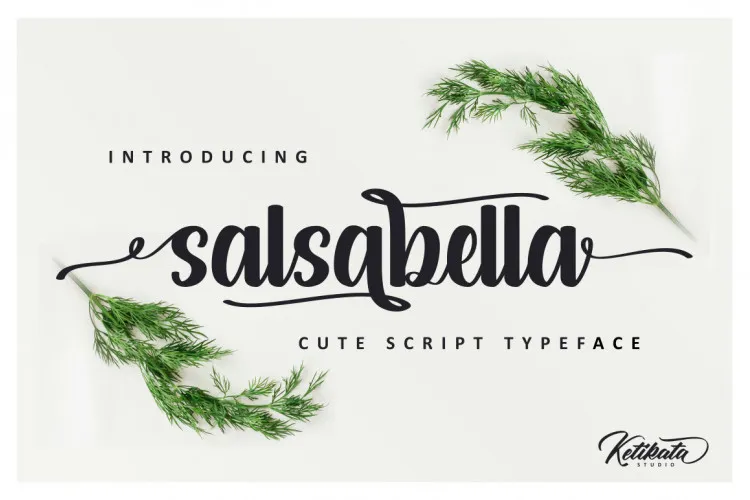
Salsabella Cute Script Font – Download Grátis
Aqui está uma descrição envolvente para a página de download da fonte ‘Salsabella Cute Script Font’, seguindo as regras fornecidas: Agradecemos por olhar esta fonte. É um script delicado e animado, perfeitamente harmonizado com elementos naturais e elegantes. Proporciona uma condução fluida que tornará suas criações singelas e sofisticadas. Introduzimos Salsabella Cute Script Font: um tipo moderno e encantador com muitos alternativos estilizados para seus projetos belíssimos. O autor cuidadosamente fez esta font, garantindo que cada letra se conecte perfeitamente e elegante, seja usada em alternativas ou não. Inclui swashes nas extremidades e no meio de algumas letras para facilitar a utilização. É fácil de usar, basta confiar em sua criatividade! Esta font é ótima para Logotipos, Tag Name, Frases Curta, Invitações de Casamento, Cartas de Cumprimentos, Card de Negócios e muitos outros projetos visuais. A Salsabella Cute Script Font é uma escolha perfeita para quem busca um toque especial em seus design gráficos. Com sua forma alegre e encantadora, ela adicionará sofisticação aos seus trabalhos sem comprometer seu estilo único.